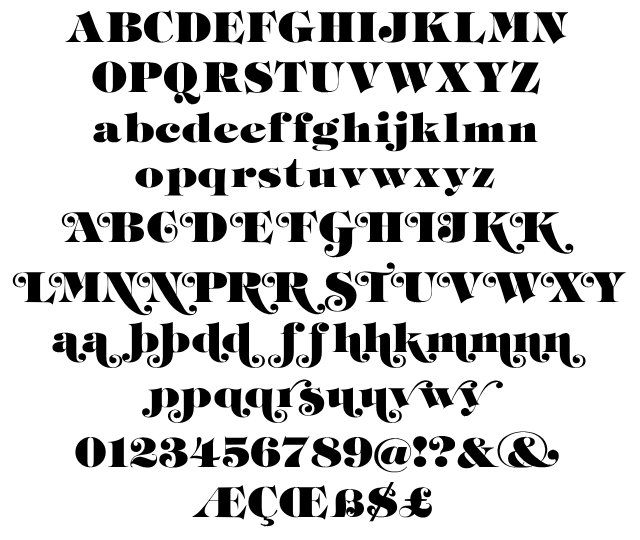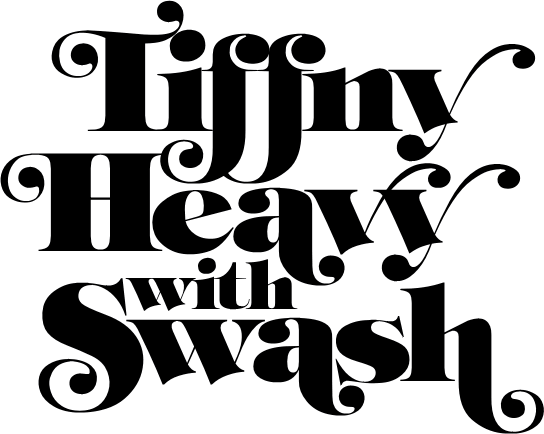
Tiffany Heavy with Swash |
Tiffany Heavy with Swash をデジタル化してみた。
以下の日記のとおり、1年半を掛けて探し回ったレア書体です。
先に Tiffany 自体をデジタル化していたので、そこへスワッシュと、
デジタル化されていなかった e, f, & のオルタネート を追加。
さらにカタログに掲載されていない独自にアレンジしたスワッシュも追加してみました。
I digitalized Tiffany Heavy with Swash. |
赤は既存の ITC Tiffany Heavy で、黒は忠実にデジタル化したもの。
全然違いますね...。
フォントメーカーからリリースされたものは、いい加減にフォント化されています(笑)
Red : Tiffany Heavy on the market
Black : Tiffany Heavy digitalized by Daylight Fonts |
ついに見つけた Tiffany with Swash!
探しはじめて1年半。
その間、いろんな書体集をチェックしましたが、やっと見つけることができました。
映画『Jackie Brown』(1997年)で使われたのが、この書体です。
ちなみに『Foxy Brown』(1974年)で使われたのは、Benguiat
Caslon Swash で、
両書体とも
Ed Benguiat によるデザイン。
I found Tiffany with Swash!
It's a wonderful type...
This type was used by Quentin Tarantino's movie "Jackie Brown" in
1997.
By the way, Benguiat
Caslon Swash to be used by "Foxy Brown" in 1974.
Ed Benguiat designed both types. |